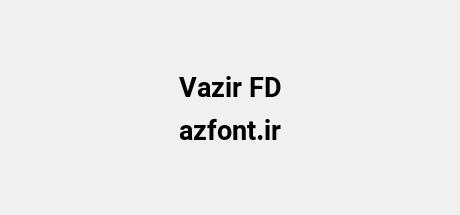
Vazir FD
فونت زیبای رایگان Vazir FD
قلم زیبای Vazir Bold FD از سری قلم های بسیار زیبا برای تایپوگرافی و لوگو تایپ می باشد.این قلم در وزن Bold-FD و توسط (Ghanem-ar.photoshop.3abber.com). 2015. All Rights Reserved طراحی و منتشر شده است.
The first version of Vazir was based on DejaVu 2.35 (was committed to the public domain) to begin designing and developing this new typeface. Non-Arabic (Latin) glyphs and data are imported from Roboto font (version 2.137; 2017) under the Apache License, Version 2.0. Non-Arabic (Latin) glyphs and data are imported from Roboto font (version 2.137; 2017) under the Apache License, Version 2.0.